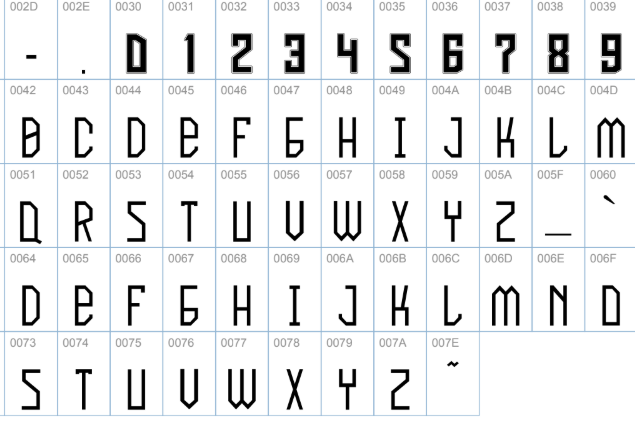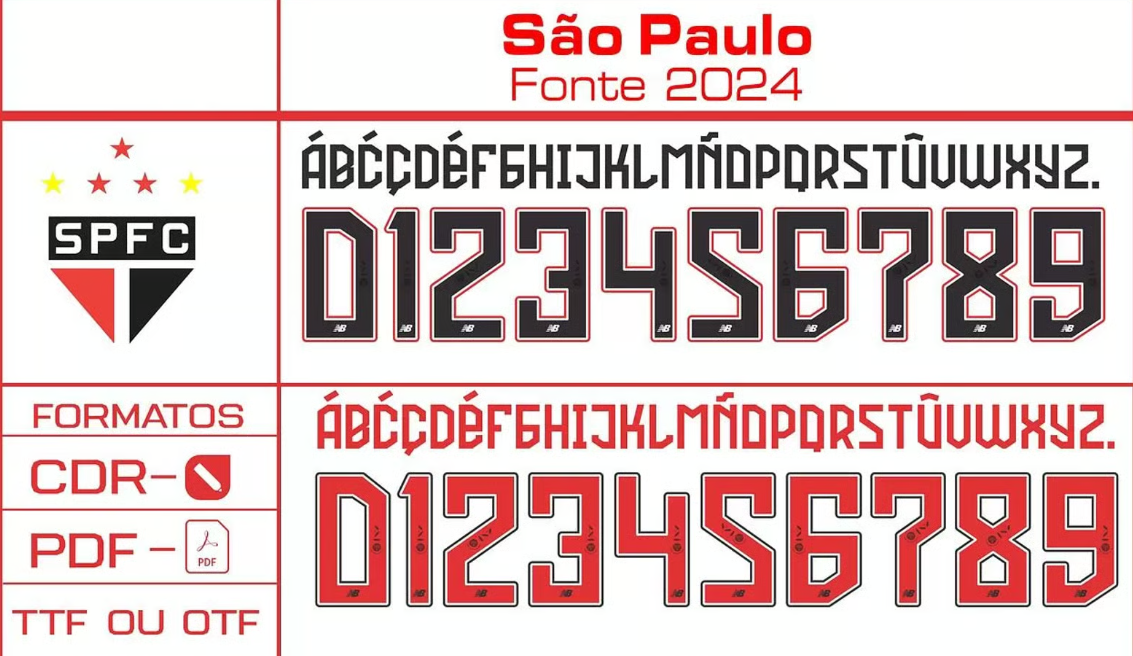
A temporada 2024 marca uma nova era para o São Paulo FC. O Tricolor Paulista iniciou sua parceria com a New Balance, substituindo a Adidas e trazendo uma identidade visual completamente renovada para os uniformes de jogo. E, claro, com uma nova fornecedora, vem uma nova tipografia.
Esta fonte exclusiva, desenhada pela New Balance, é a que estampa os nomes e números dos jogadores do SPFC ao longo da temporada. Se você é um designer, entusiasta ou simplesmente um torcedor querendo criar artes personalizadas, ter essa fonte é essencial.
Detalhes Técnicos da Fonte
- Nome Oficial: Fonte São Paulo 2024 (Padrão New Balance)
O Estilo Visual da Fonte
A tipografia da New Balance para o São Paulo em 2024 é marcada pela modernidade e impacto. É uma fonte sans-serif (sem serifa) robusta, com linhas retas e cortes angulares precisos, que transmitem uma sensação de velocidade e força.
Diferente das fontes mais arredondadas da Adidas em anos anteriores, o novo design da New Balance é mais “agressivo” e imponente. Ela é usada em todos os uniformes de jogo (Home, Away e Alternativo) da temporada, garantindo excelente legibilidade tanto no campo quanto na tela.